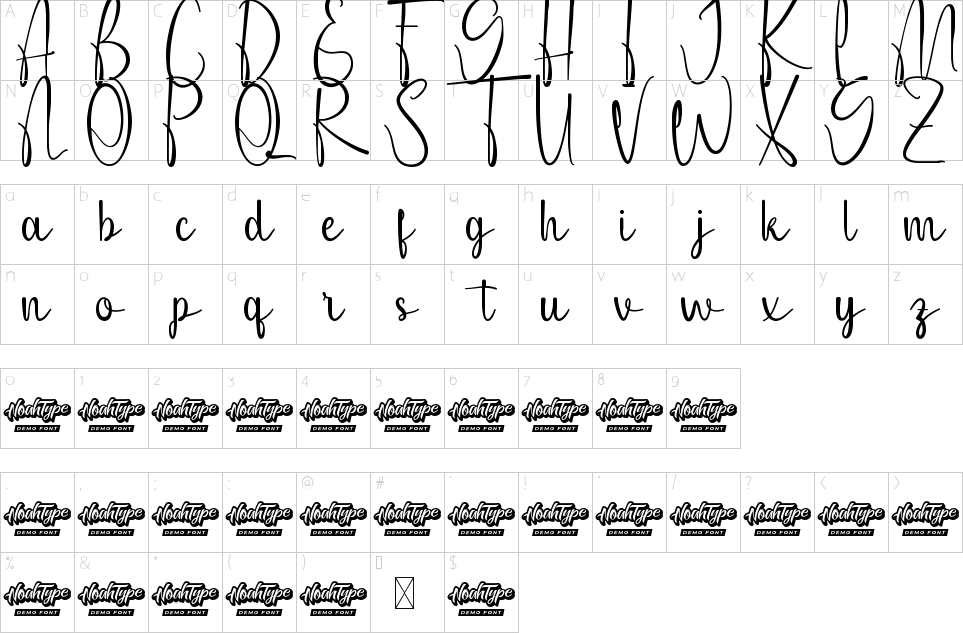
Descubra a beleza da Mix Match Font, uma opção gratuita e versátil para personalizar seus projetos. Desenhada pelo designer indeterminado na NoahType, Mix Match traz uma paleta de caracteres fluidos e agradáveis ao seu trabalho, tornando-a uma escolha inteligente para designers gráficos e criativos. Com uma alta popularidade, a fonte Mix Match já foi baixada por 2,242 pessoas, demonstrando sua relevância e qualidade. Se você está buscando uma fonte moderna e fácil de usar que não comprometa sua criatividade, a Mix Match é a escolha perfeita. Descubra a diferença que Mix Match pode fazer em seus projetos!